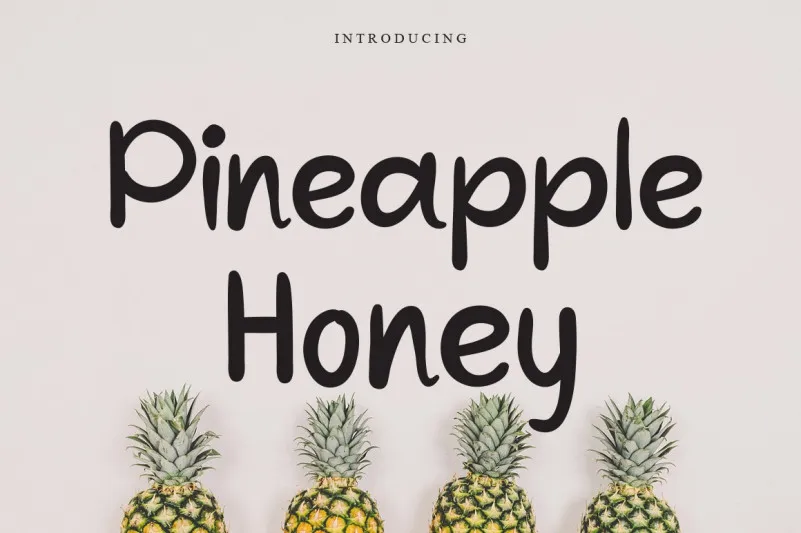
Pineapple Honey Font – Download Grátis
Esta é uma fonte elegante, fina e escrita a mão cursiva. Ela se destaca por sua delicadeza e graça, fazendo dela uma escolha perfeita para qualquer projeto. Este suave estilo trará um toque alegre à cada página que você criar. Ideal para designers que buscam uma fonte agradável e versátil, ela combina harmoniosamente com diversas ideias de design, tornando-a uma opção indispensável na sua biblioteca de fontes. A Pineapple Honey Font é perfeita para quando você precisa dar um toque jovial ou delicado em qualquer projeto. Com esse traço curvilíneo e fresco, a Pineapple Honey Font se destaca como uma excelente opção para aqueles que desejam adicionar um ar de graça aos seus designs. Seja em cartões de aniversário coloridos, logotipos vibrantes ou simplesmente texturas sofisticadas para elementos de e-mail personalizados, essa fonte trará alegria e frescor ao seu trabalho.